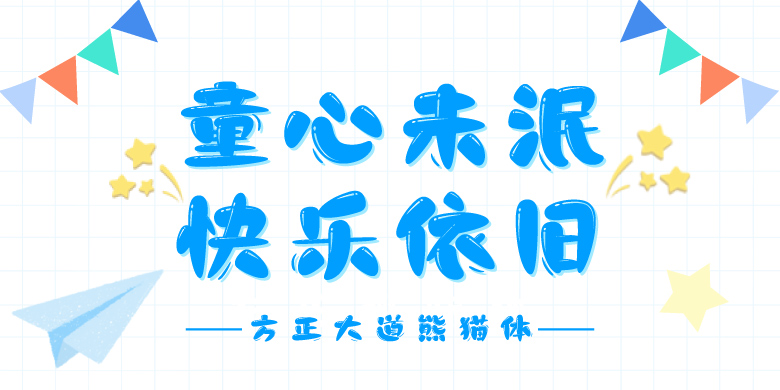
方正大道熊猫体
字体品牌: 方正字库 设计师: 李强 字体分类: 创意字体 字体属性: 精品字 字符集: 大陆简体(GB2312-80) 发布时间: 2022
文字笔画中有显著的粗细对比,能够增强文字的记忆度。在笔画设定上,起笔圆润收笔细,且在笔画中加入了高亮和动感的修饰线条,体现圆嘟嘟但又不失灵动的感觉。
在设计字样的过程中,感觉这套字特别像“熊猫”,粗的笔画和留白空间形成了熊猫的主体,“短点”笔画形成眼睛或脚印。细笔画是竹子,动感修饰笔画是掉落的竹叶,故命名“熊猫体”。